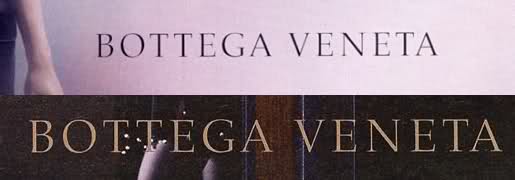
[feine Serife] Typo von "Bottega Veneta" gesucht
weiß einer von Euch welche Schrift im Logo von "Bottega Veneta" verwendet wird? Mit diesen feinen Serifen? Oder kennt jemand eine ähnliche?
Nur ähnlich, was die Strichstärken angeht:
Die Tiemann ist eine rein classicistische; das Muster scheint, soweit ich das bei der Größe erkennen kann, einen Batsard-Einschlag zu haben.
Palatino. (Nur ein wenig schmaler und dünner.)